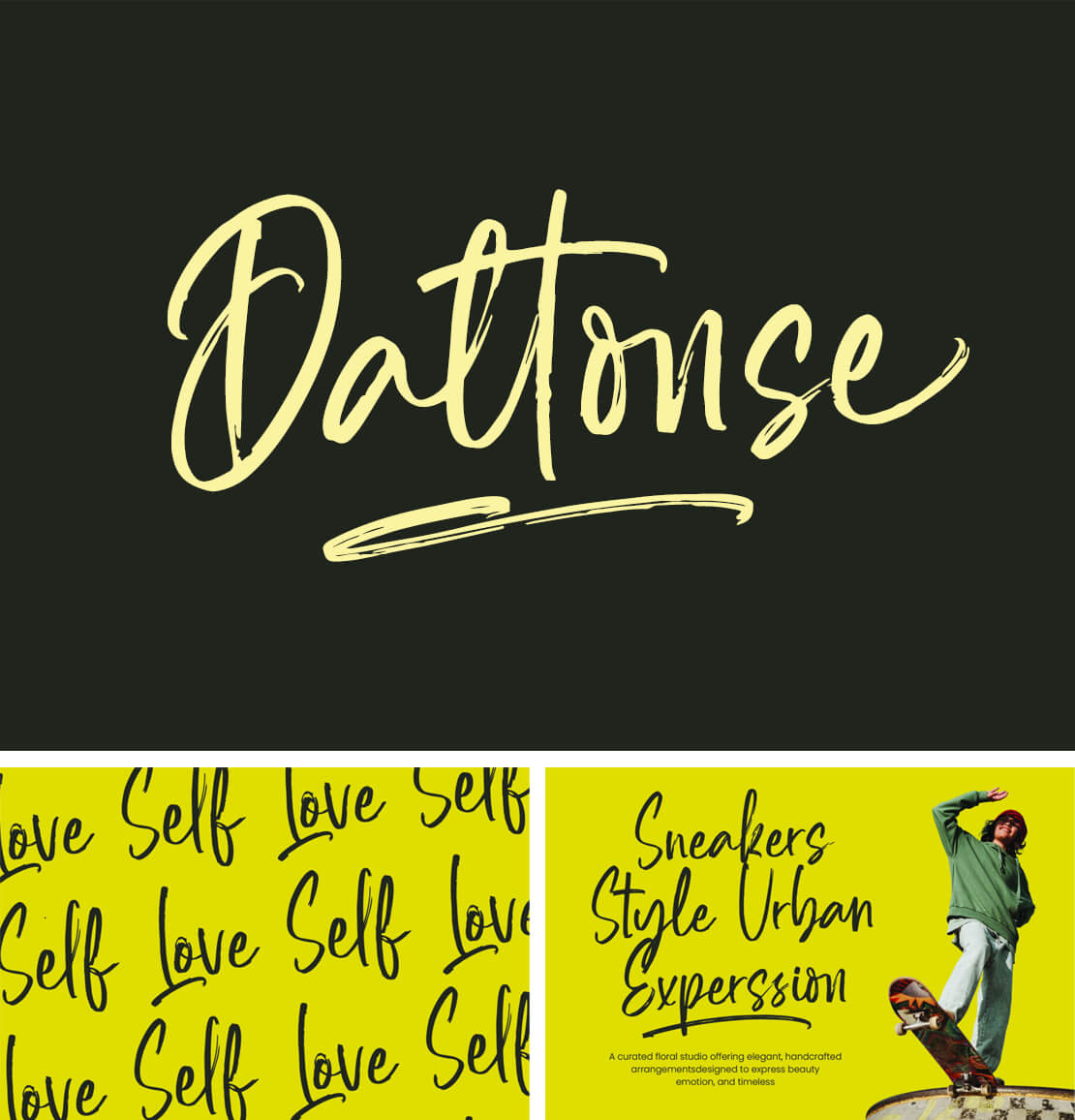
Daltonse
Eine markante Pinsel-Schreibschrift mit dynamischer Strichführung. »Daltonse« von Letterena Studios steht kostenlos zum Herunterladen bereit.
Das Schriftbild von »Daltonse« zeichnet sich durch einen schwungvollen und handgemachten Brush-Charakter aus. Der Zeichensatz umfasst insgesamt 420 Glyphen und bietet u.a. 101 Ligaturen, 52 alternative Buchstabenformen, deutsche Umlaute sowie acht typografische Schwünge (Swashes).